一、书法标准字体
书法是我国具有三千多年历史的汉字表现艺术的主要形式,既有艺术性,又有实用性。目前,我国一些企业主用政坛要人、社会名流及书法家的题字,作企业名称或品牌标准字体,比如:中国国际航空公司、健力宝等。
有些设计师尝试设计书法字体作为品牌名称,有特定的视觉效果,活泼、新颖、画面富有变化。但是,书法字体也会给视觉系统设计带来一定困难。首先是与商标图案相配的协调性问题,其次是是否便于迅速识别。
书法字体设计,是相对标准印刷字体而言,设计形式可分为两种。一种是针对名人题字进行调整编排,如中国银行、中国农业银行的标准率体。另一种是设计书法体或者说是装饰性的书法体,是为了突出视觉个性,特意描绘的字体,这种字体是以书法技巧为基础而设计的,介于书法和描绘之间。
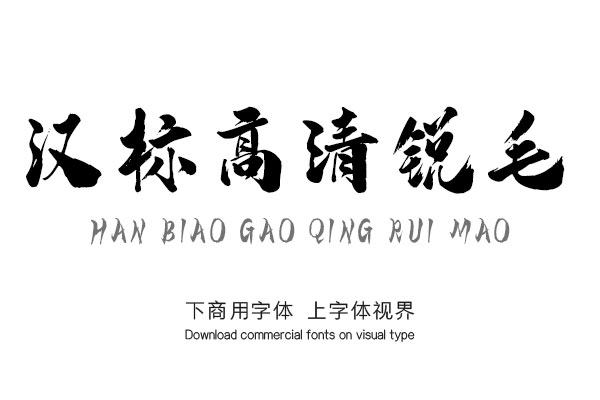
二、装饰标准字体
装饰字体在视觉识别系统中,具有美观大方,便于阅读和识别,应用范围广等优点。海尔,科龙的中文标准字体即属于这类装饰字体设计。
装饰字体是在基本字形的基础进行装饰、变化加工而成的。它的特征是在一定程度上摆脱了印刷字体的字形和笔划的约束,根据品牌或企业经营性质的需要进行设计,达到加强文字的精神含义和富于感染力的目的。
装饰字体表达的含意丰富多彩。如:细线构成的字体,容易使人联想到香水、化妆品之类的产品,园厚柔滑的字体,常用于表现食品、饮料、洗涤用品等;而浑厚粗实的字体则常用于表现企业的实力强劲;而有棱角的字体,则易展示企业个性等等。
总之,装饰字体设计离不开产品属性和企业经营性质,所有的设计手段都必须为企业形象的核心一-标志服务。它运用夸张、明暗、增减笔划形象、装饰等手法,以丰富的想象力,重新构成字形,既加强文字的特征,又丰富了标准字体的内涵。同时,在设计过程中,不仅要求单个字形美观,还要使整体风格和谐统一,理念内涵和易读性,以便于信息传播。
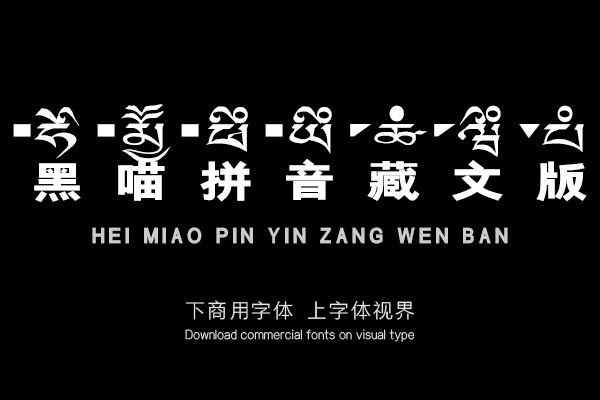
三、英文标准字体
企业名称和品牌标准字体的设计,一般均采用中英两种文字,以便于同国际接轨,参与国际市场竞争。
和装饰体。书法体的设计虽然很有个性、很美观,但识别性差,用于标准字体的不常见,常见的情况是用于人名,或非常简短的商品名称。装饰字体的设计,应用范围非常广泛。从设计的角度看,英文字体根据其形态特征和设计表现手法,大致可以分为四类:一是等线英文字体(包括汉语拼音)的设计,与中文汉字设计一样,也可分为两种基本字体,即书法体
体,字形的特点几乎都是由相等的线条构成;二是书法体,字形的特点活泼自由、显示风格个性;三是装饰体,对各种字体进行装饰设计,变化加工,达到引人注目,富于感染力的艺术效果;四是光学体,是摄影特技和印刷用网绞技术原理构成。